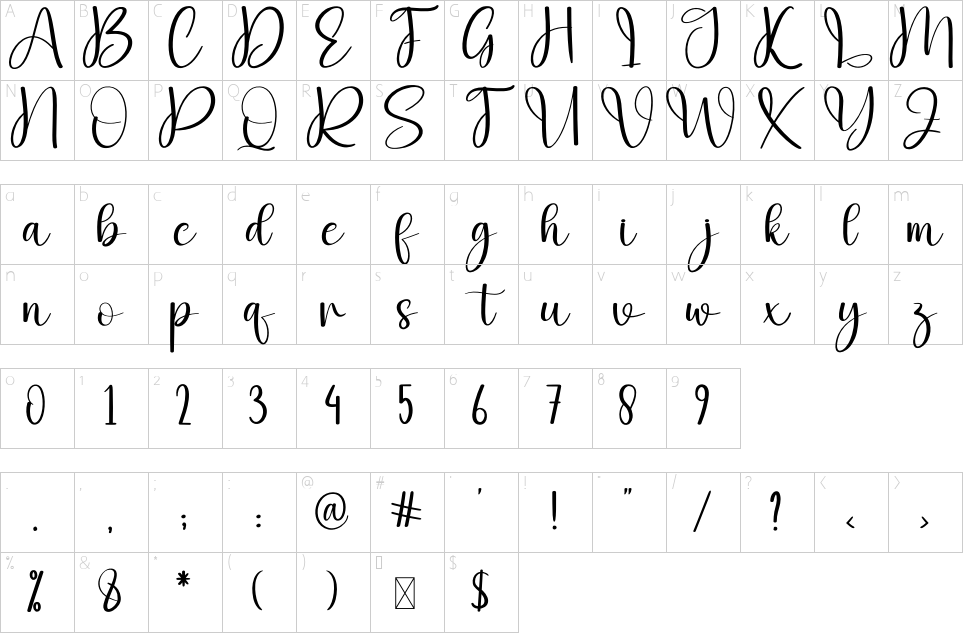
Aqui está uma descrição em português para a página de download da fonte ‘Sadnight Font | 1001 Free Fonts’, mantendo a essência da descrição original e seguindo as regras fornecidas: A fonte Sadnight é uma criação de scratchones, disponível para Windows e Mac em seu catálogo de fontes gratuitas. Esta fonte, cheia de personalidade e graça, é perfeita para quem busca uma fonte alegre e vibrante para seus projetos. Com um design criativo e original, Sadnight é ideal para adicionar um toque agradável e único aos textos de seus projetos. Sua alta popularidade demonstra a qualidade e originalidade desta fonte, que já foi baixada 301 vezes. Seja você um designer gráfico, um web designer ou um profissional de marketing, Sadnight é uma excelente opção para adicionar um toque especial ao seu trabalho. Descubra e baixe sua própria cópia da fonte Sadnight gratuitamente.